除了自动为成对调整查找创建字距对外,FontCreator 还可以自动向字体添加许多其他 OpenType 布局功能。请确保您的字形具有友好名称,如此处所述。在 OpenType 设计器窗口中,单击左上角的第一个图标。您现在可以选择要生成和/或更新的功能。
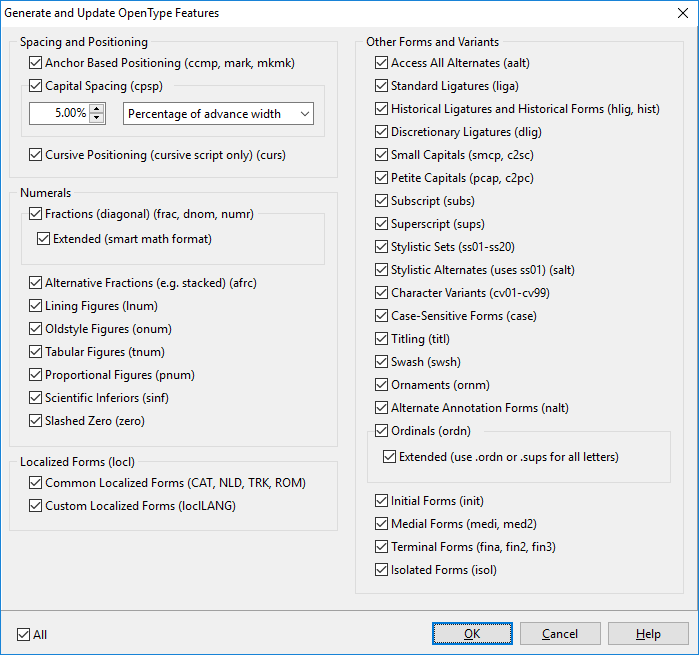
生成的查找和类具有以脚本缩写开头的名称。例如,latn_liga 用于标准基于拉丁语的连字。更新功能时,现有的查找和类将被删除,因此如果您添加自定义功能,最好避免将它们与生成的功能混合。
注意:希腊语和西里尔字符与拉丁语(latn)分组在一起。
除非另有说明,否则功能和查找的生成仅限于拉丁语、希腊语和西里尔语脚本。
基于锚点的定位 (ccmp, mark, mkmk)
相对于标记和基础字形定位标记字形,并组合和替换多个字形。
如果您的字体包含带有锚点的字形,则可以根据这些锚点生成定位功能。使用完成复合字形自动生成锚点并基于这些锚点构建复合字形。
如果您想为大写和小写字母使用不同的标记,请添加带有 .case 后缀的标记变体。如果您需要窄字母(如 i 和 j)的特殊标记,请创建带有 .narrow 后缀的附加标记字形。如果您想要小型大写字母的附加标记,请使用 .smcp;对于小型大写字母,请使用 .pcap。如果您想为小型大写字母和小型大写字母都使用标记,请添加带有 .cap 后缀的标记。
大写间距 (cpsp)
全局调整全大写文本的字形间距。大多数字体包含大写和小写字符,并且大写字符定位为与小写字符一起工作。当大写字母用于单词时,它们之间需要更多的空间以提高可读性和美观性。
您可以选择通过为每个字形的进宽度添加统一的百分比(根据规范推荐)来增加空间,或者通过 upem 的百分比指示的固定值。
草书定位 (curs)
在阿拉伯语等草书脚本中,此功能草书定位相邻字形。
此功能用于草书脚本,将利用入口和出口锚点。对于草书脚本,请确保每个初始字形具有出口锚点,每个中间字形具有入口和出口锚点,每个最终字形具有入口锚点。
分数(对角线)(frac)
用对角线分数替换用斜杠分隔的数字。如果选择了扩展选项,它将生成带有上下文替换的查找。
要使此功能工作,需要以下字形:
数字(零到九),以及可选的 parenleft、parenright、hyphenminus、minus、plus 等,以及带有后缀 .dnom、.subs 或 inferior 的分母变体,以及带有 .numr、sups 或 superior 的分子变体。至少数字必须具有相同的后缀,但通常最好对所有分母使用相同的后缀,对所有分子使用相同的后缀。
还需要斜杠和分数;可选的是空格和细空格。
如果并非所有必需的字形都可用,或者如果未选择扩展选项,它将创建带有以下预组合分数的连字查找:
onehalf, zerothirds, onethird, twothirds, onequarter, threequarters, onefifth, twofifths, threefifths, fourfifths, onesixth, fivesixths, oneseventh, oneeighth, threeeighths, fiveeighths, seveneighths, oneninth, 和 onetenth。
替代分数 (afrc)
用替代形式替换用斜杠分隔的数字;通常是堆叠/螺母分数。
将为这些字形生成连字查找:
onehalf.afrc, onethird.afrc, twothirds.afrc, onequarter.afrc, threequarters.afrc, onefifth.afrc, twofifths.afrc, threefifths.afrc, fourfifths.afrc, onesixth.afrc, fivesixths.afrc, oneseventh.afrc, twosevenths.afrc, threesevenths.afrc, foursevenths.afrc, fivesevenths.afrc, sixsevenths.afrc, oneeighth.afrc, threeeighths.afrc, fiveeighths.afrc, seveneighths.afrc, oneninth.afrc, twoninths.afrc, fourninths.afrc, fiveninths.afrc, sevenninths.afrc, eightninths.afrc, onetenth.afrc, threetenths.afrc, seventenths.afrc, ninetenths.afrc, onesixteenth.afrc, threesixteenths.afrc, fivesixteenths.afrc, sevensixteenths.afrc, ninesixteenths.afrc, elevensixteenths.afrc, thirteensixteenths.afrc, fifteensixteenths.afrc, onethirtysecond.afrc, threethirtyseconds.afrc, fivethirtyseconds.afrc, seventhirtyseconds.afrc, ninethirtyseconds.afrc, eleventhirtyseconds.afrc, thirteenthirtyseconds.afrc, fifteenthirtyseconds.afrc, seventeenthirtyseconds.afrc, nineteenthirtyseconds.afrc, twentyonethirtyseconds.afrc, twentythreethirtyseconds.afrc, twentyfivethirtyseconds.afrc, twentyseventhirtyseconds.afrc, twentyninethirtyseconds.afrc, thirtyonethirtyseconds.afrc, onesixtyfourth.afrc, threesixtyfourths.afrc, fivesixtyfourths.afrc, sevensixtyfourths.afrc, ninesixtyfourths.afrc, elevensixtyfourths.afrc, thirteensixtyfourths.afrc, fifteensixtyfourths.afrc, seventeensixtyfourths.afrc, nineteensixtyfourths.afrc, twentyonesixtyfourths.afrc, twentythreesixtyfourths.afrc, twentyfivesixtyfourths.afrc, twentysevensixtyfourths.afrc, twentyninesixtyfourths.afrc, thirtyonesixtyfourths.afrc, thirtythreesixtyfourths.afrc, thirtyfivesixtyfourths.afrc, thirtysevensixtyfourths.afrc, thirtyninesixtyfourths.afrc, fortyonesixtyfourths.afrc, fortythreesixtyfourths.afrc, fortyfivesixtyfourths.afrc, fortysevensixtyfourths.afrc, fortyninesixtyfourths.afrc, fiftyonesixtyfourths.afrc, fiftythreesixtyfourths.afrc, fiftyfivesixtyfourths.afrc, fiftysevensixtyfourths.afrc, fiftyninesixtyfourths.afrc, sixtyonesixtyfourths.afrc, sixtythreesixtyfourths.afrc。
lining Figures (lnum)
此功能用 lining figures 替换选定的非 lining figures。设计用于与数字一起使用的各种字符也可能具有 lining 版本,例如 plus.lnum、equal.lnum、multiply.lnum、divide.lnum 等。
Oldstyle Figures (onum)
此功能将默认或 lining 样式的选定数字替换为 Oldstyle 形式。设计用于与数字一起使用的各种字符也可能具有 Oldstyle 版本。
Tabular Figures (tnum)
此功能用设置在统一(表格)宽度上的相应字形替换设置在比例宽度上的数字字形。表格宽度通常是默认值。
否则添加这些:
Proportional Figures (pnum)
此功能用设置在字形特定(比例)宽度上的相应字形替换设置在统一(表格)宽度上的数字。
否则添加这些:
Figure it out!
要使上述四个功能在默认数字是 lining 表格数字时协同工作,您需要添加所有这些:
1. zero-nine.onum (Oldstyle 表格数字)
2. zero-nine.pnum (Lining 比例数字)
3. zero-nine.onum.pnum (Oldstyle 比例数字)
Scientific Inferiors (sinf)
用 inferior figures 替换 lining 或 Oldstyle figures(低于标准基线的较小字形,主要用于化学或数学符号)。也可能用字母 inferior 替换小写字符。
适用于带有后缀 .sinf(例如 five.sinf)或 inferior(sixinferior)的字形变体。
Slashed Zero (zero)
用替代形式替换零的默认形式,例如,使用对角线穿过计数器来区分 0 和 O(零和大写 O)。
适用于带有后缀 .zero(例如 zero.zero)的字形变体。
Localized Forms (locl)
用于在广阔地理区域书写多种语言的许多脚本已经开发了特定字母的本地化变体形式,这些形式由各个文学社区使用。例如,保加利亚语和塞尔维亚语字母中的许多字母具有与其俄语对应字母以及彼此不同的形式。在某些情况下,本地化形式与脚本"规范"仅略有不同,在其他情况下,形式完全不同。此功能使能够用本地化形式替换默认形式。
常见的本地化形式包括:
"iacute j"的组合在几种语言中很常见(例如西班牙语市镇 Níjar),但在荷兰语单词中 i 和 j 属于一起,因此两者在基础字符上方都有点或重音。然而 jacute 不是 Unicode 的一部分,因此该字符不存在。为了在荷兰语文本中正确使用,字体可以利用 locl 功能。
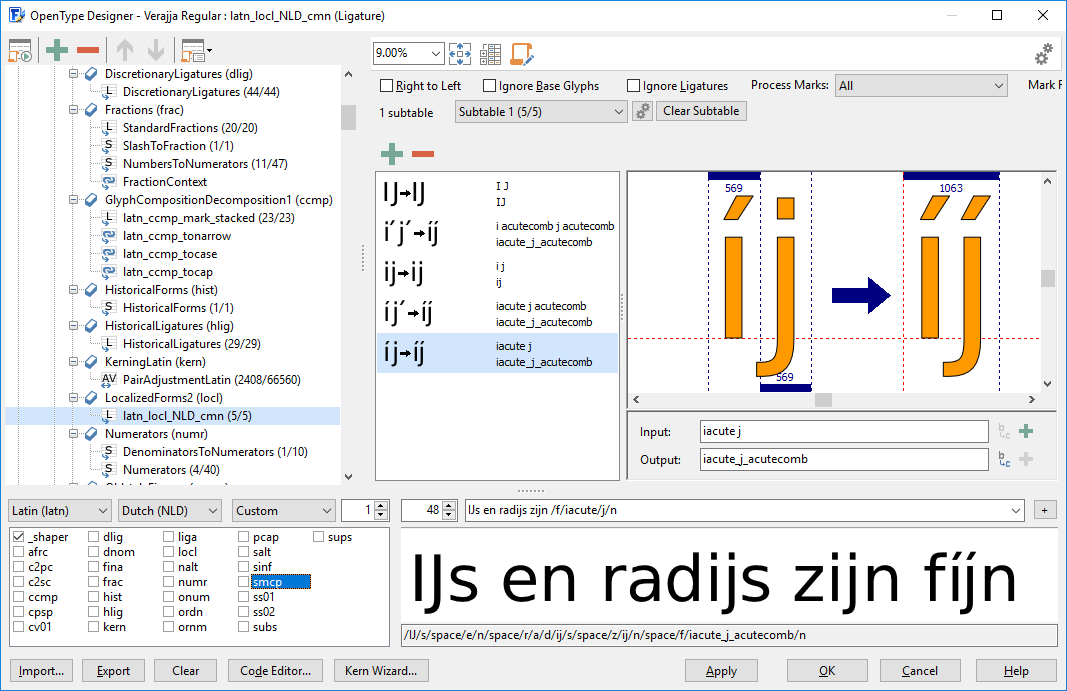
自定义本地化形式使用带有 .loclLANG 后缀的字形来覆盖本地化替换和连字。在此上下文中,LANG 是一个或多个由下划线分隔的语言标记。例如 A.loclFRA 或 B.loclENG_ESP。目前仅支持基于拉丁语的语言标记,以及希腊语(ELL)、西里尔语(SRB、BGR)、阿拉伯语(ARA)和希伯来语(IWR)。某些字体可能会受益于波兰语形式,因为字母 ć、ń、ó、ś、ź 使用 kreska(波兰语字母中使用的变音符号,图形上类似于重音)。为此类本地化形式添加字形,将它们命名为 Sacute.loclPLK 等。
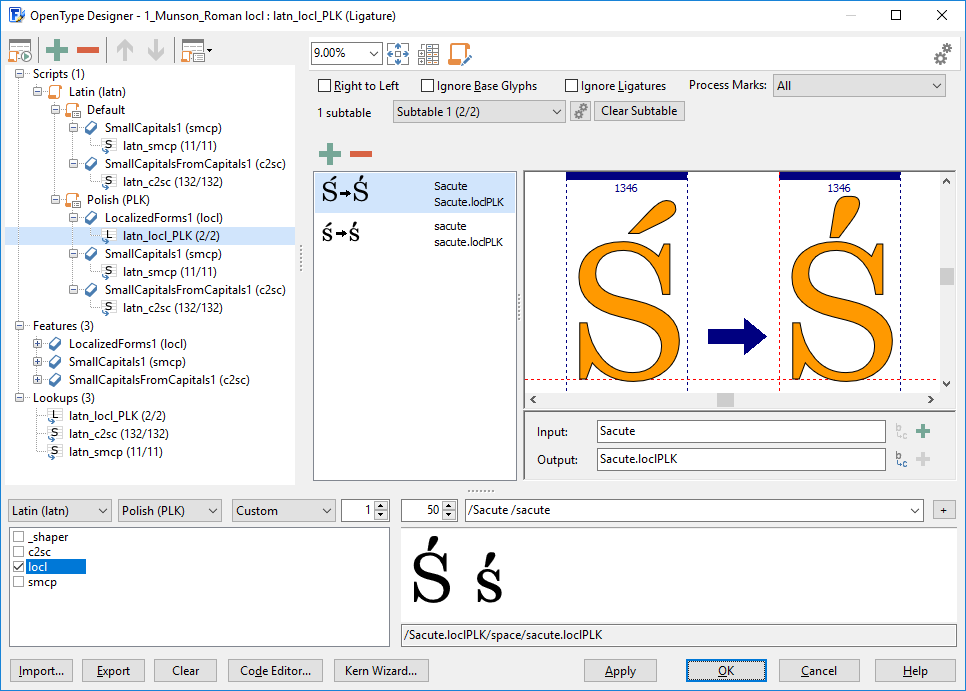
提示:使用测试 Web 字体(CTRL + F5)在 Web 字体测试页面上测试字体。要在 Word 中启用本地化形式;选择文本,应用正确的字体,并确保您至少激活了标准连字。最后选择正确的语言。要在 InDesign 中启用它,在字符面板上选择语言。您还可以在 FontCreator 的预览面板中测试本地化形式,只需确保您选择了正确的脚本和语言,如上所示。
Access All Alternates (aalt)
此功能使选定字符的所有变体可访问。
适用于带有所有后缀的字形变体。
Standard Ligatures (liga)
此功能用于将字形映射到其可选连字形式。它用单个字形替换字形序列,该字形因排版目的而首选。
此功能涵盖这些连字以及所有带有 .liga 后缀的字形:
ff, fi, fl, ffi, 和 ffl
注意:默认情况下,整形引擎应处理 liga 功能,但用户应该能够停用它。如果字体有应该始终形成的连字,请在 rlig 中定义它们。
Historical Ligatures and Historical Forms (hlig, hist)
用单个字形替换字形序列,该字形因排版目的而首选。
此功能为 s 的长形式(longs)向 hist 添加替换,并将默认(当前)形式替换为历史替代形式以 hlig 所有带有 .hlig 后缀的字形。
Discretionary Ligatures (dlig)
用单个字形替换字形序列,覆盖可能用于特殊效果的连字。
此功能涵盖带有 .dlig 后缀的连字字形。
注意:默认情况下不处理此功能,但用户可以激活它。
Small Capitals (smcp, c2sc)
此选项将字符转换为小型大写字母。
此功能涵盖带有以下后缀之一的字形:.smcp .c2sc .sc
我们建议对小写和大写都使用小写字符名称,因此如果您定义了 a.smcp,它将在 smcp 功能(a → a.smcp)和 c2sc 功能(A → a.smcp)中使用。如果您需要区分大写和小写替换,则定义两个变体。例如,对于 germandbls(德国字母 Eszett)。
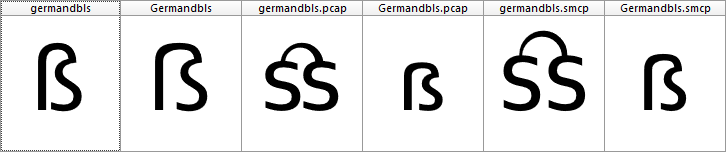
您还可以通过添加多个后缀来组合功能。如果您还包括本地化小型大写字母,请将它们命名为 sacute.loclPLK.smcp 等。
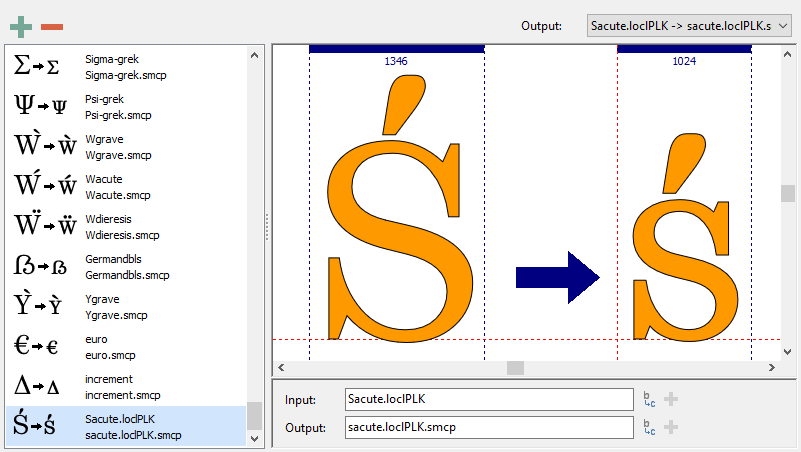
Petite Capitals (pcap, c2pc)
此选项将字符转换为小型大写字母。这种额外的大写字母大小,比常规小型大写字母更短,使具有小写 x 高度的字体能够比更高的常规小型大写字母更好地与小写文本协调。
此功能涵盖带有以下后缀之一的字形:.pcap .c2pc .pc
与小型大写字母类似,我们建议使用小写字符名称,例如 a.pcap
Subscript (subs)
用下标字形替换默认字形。
适用于带有后缀 .subs(例如 four.subs)或 inferior(fourinferior)的字形变体。
Superscript (sups)
用上标字形替换默认字形。
适用于带有后缀 .sups(例如 four.sups)或 superior(foursuperior)的字形变体。
Stylistic Sets (ss01-ss20)
这些允许与字符集部分对应的样式变体字形集,例如拉丁字体中小写字母的多个变体。
此功能涵盖带有以下后缀之一的字形:.ss01 .ss02 等。
注意:FontCreator 支持样式集的功能参数。
Stylistic Alternates (salt)
此功能链接到与样式集 01 (latn_ss01) 使用的相同替换查找。
将为带有 .salt 后缀的字形添加额外的替换查找。
Character Variants (cv01-cv99)
字符变体功能应仅适用于一个字符或以这种方式密切相关的字符集。
此功能涵盖带有以下后缀之一的字形:.cv01 .cv02 等。如果给定字符有多个替代,请添加额外的后缀。例如,如果您有拉丁大写字母 Agrave 的三个不同变体,并希望将它们包含在 cv01 中,这将起作用:
Agrave.cv01
Agrave.cv01.modern
Agrave.cv01.yourdescription
注意:FontCreator 支持字符变体的功能参数。
Case-Sensitive Forms (case)
主要用于将各种标点符号向上移动到与全大写序列或 lining 数字集一起使用效果更好的位置。
适用于带有 .case 后缀的字形变体。
Titling (titl)
用专门为标题设计的相应形式替换默认字形。这些可能是全大写和/或主体更大,并针对更大尺寸的查看进行了调整。
适用于带有 .titl 后缀的字形变体。
Swash (swsh)
用相应的 swash 字形替换默认字符字形。请注意,给定字符可能有多个 swash 替代形式。
此功能涵盖带有 .swsh 后缀的字形。与字符变体的方法类似;如果您对给定字符有多个替代,请在 .swsh 之后添加额外的后缀。
Ornaments (ornm)
这生成双重功能功能,使用两种输入方法让用户可以访问字体中的装饰字形(例如 fleurons、dingbats 和边框元素)。一种方法用完整可用装饰集的选择替换项目符号字符($2022);另一种用分配给它们的装饰替换字母数字字符(A-Z 和 a-z)。第一种方法支持一般或浏览用户;第二种方法支持高级用户。
适用于带有后缀 .ornm(例如 a.ornm)的字形变体。第一种方法需要项目符号字符($2022)。第二种方法需要字母数字字符及其相应的 .ornm 变体。
Alternate Annotation Forms (nalt)
用各种注释形式(例如放置在开放或实心圆圈、正方形、括号、菱形或圆角框中的字形)替换默认字形。
此功能涵盖带有 .nalt 后缀的字形。如果字体不包含 .nalt 字形,此功能将基于 Unicode 块封闭字母数字中定义的圆形字符生成,例如 oneCircled。
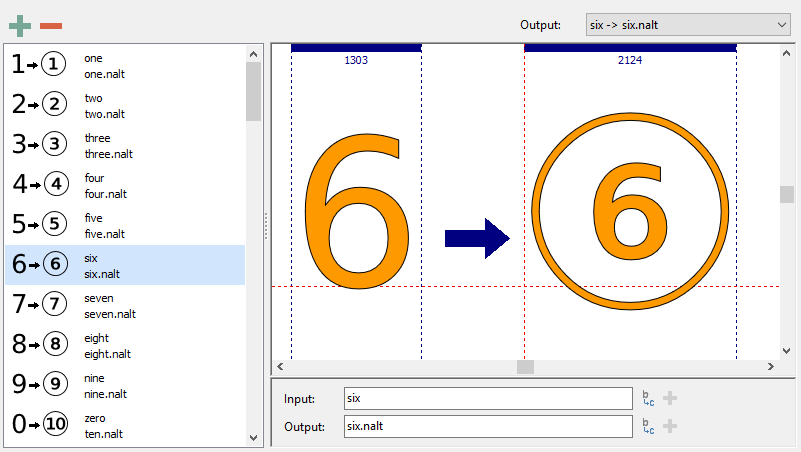
Ordinals (ordn)
用相应的序数形式替换默认字母字形,用于数字之后。它使用连字查找将"No."或"No"替换为 numero 字符($2116)。
"numero"连同"N"、"o"和"."是连字查找所必需的。
扩展选项使用带有 .ordn 后缀的字形,否则它将为 a 和 A 添加替换到 ordfeminine($AA),以及 o 和 O 到 ordmasculine($BA)。
Initial, Medial, Terminal, and Isolated Forms (init, medi, fina, isol, med2, fin2, fin3)
当出现在初始上下文中时,用替代形式替换具有适用连接属性的字符的字形。
这些形式不应用于拉丁语脚本,而是用于阿拉伯语和其他利用连接属性的脚本。
为您希望覆盖的字形添加适当的后缀。某些字符已经带有正确的后缀以使用这些选项,例如 beeh-arab.init 和 veh-arab.fina。
注意:功能 med2、fin2 和 fin3 仅用于叙利亚语脚本。